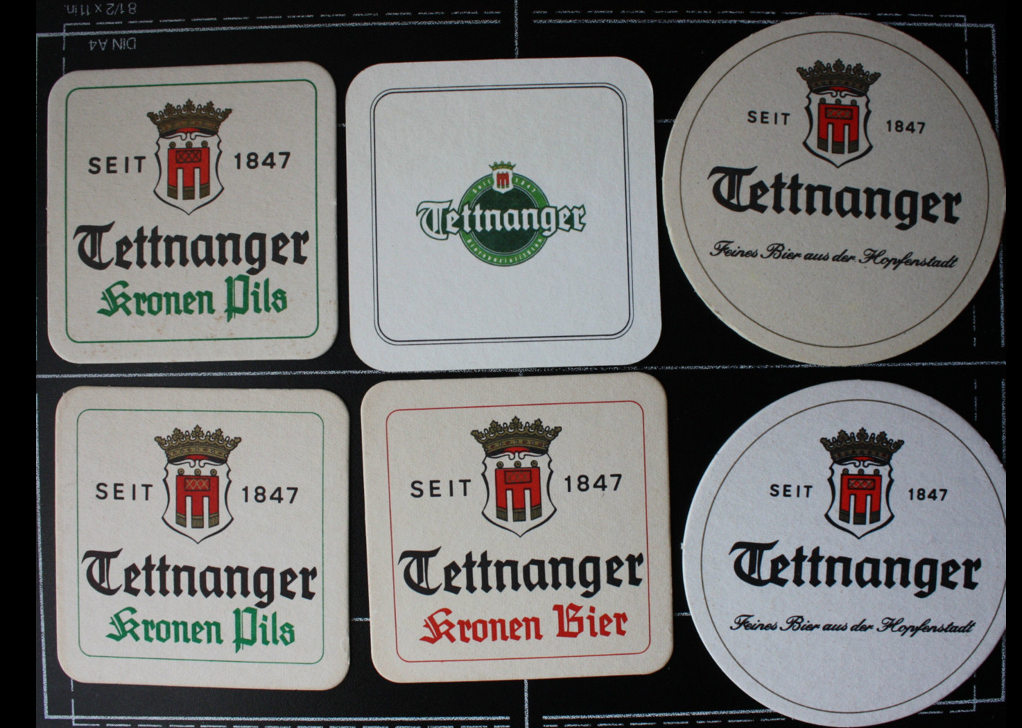
Frakturschrift (Tettnanger)
Wir haben von einem Kunden eine Wortmarke ( Tettnanger Krone ) und ich möchte gerne ausfindig machen, wie die Frakturschrift heißt, die dafür verwendet wurde.  Es ist möglich, dass sie in der Vergangenheit bereits verändert wurde.  Kann mir jemand einen Tip geben, wo ich recherchieren könnte? Oder kennt vielleicht sogar jemand die Schrift?
Bei einigen der Bierdeckel ist das recht gut zu erkennen, das dies eine Handzeichnung ist, die e und n sind nicht 100% deckungsgleich, mittlerweile dürfte das Logo digital nachgezeichnet worden sein, und hier macht man sich das halt einfacher, und kiopiert doppelte Buchstaben.